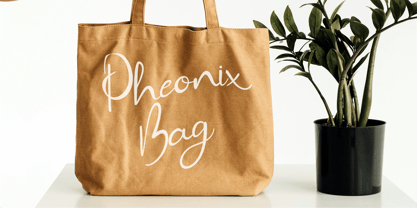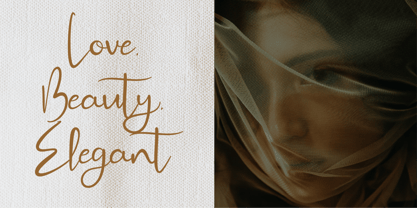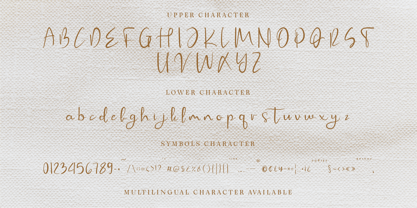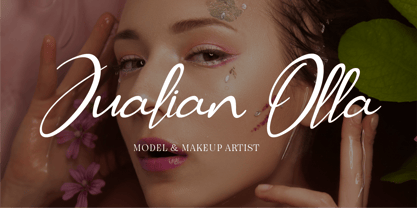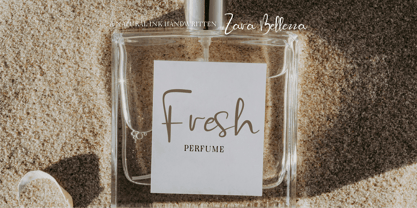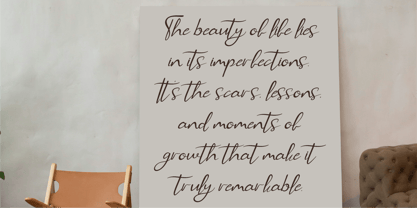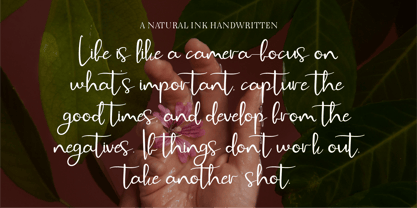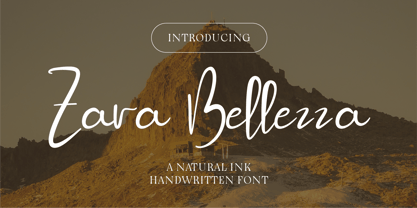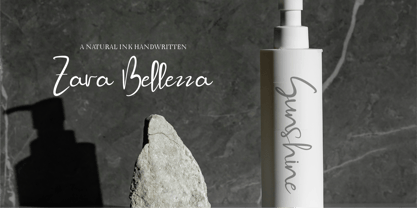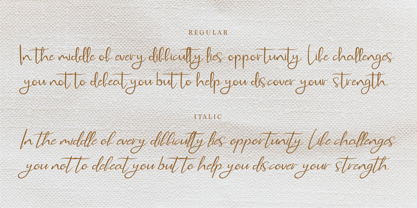
CF Zara Bellezza
La familia tipográfica CF Zara Bellezza fue diseñada por Gilang Mei Nugraha, Frederik Aristaputra y publicada por Indotype. CF Zara Bellezza contiene 2 estilos y opciones de paquete familiar. Más información sobre esta familia
Sylara Signates is an exquisite pen-inked handwritten font, beautifully capturing the essence of authentic signatures. With its elegant curves, smooth flow, and natural handcrafted strokes, this font brings a sophisticated yet approachable look. Designed to emulate the luxury of ink on paper, it is perfect for branding, wedding invitations, logos, and personal designs. Whether you're crafting a heartfelt message or creating professional designs, Sylara Signates delivers timeless charm and refined elegance, leaving a lasting impression.